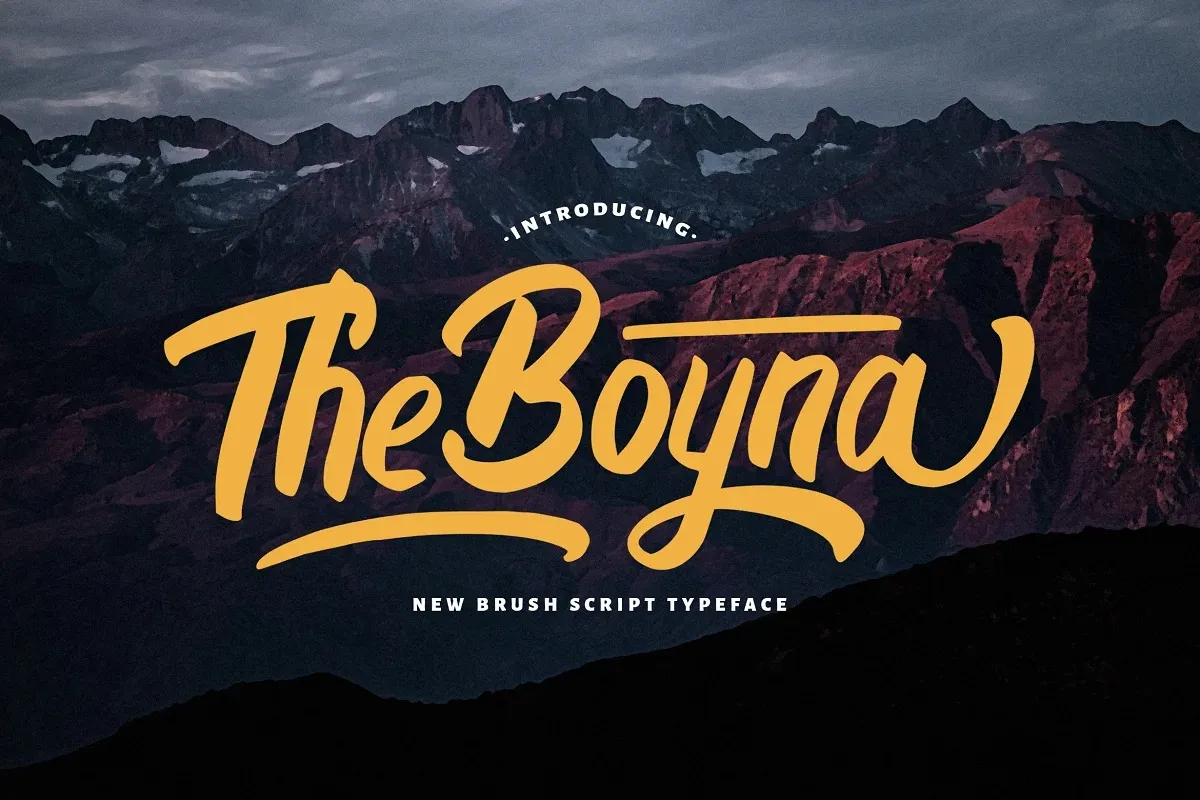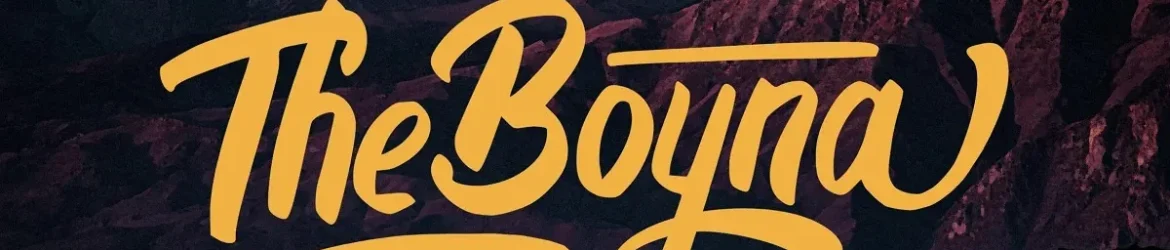
A ‘Boyna Font’ é uma aquarela script feita para quem busca uma escrita natural e casual, ideal para ambientes criativos e versáteis. Escrevida com pincéis sobre papel, então cuidadosamente trazida de volta à forma vetorial, essa fonte possui letras curvadas, arredondadas e carrega um estilo vintage único e sofisticado. Suas linhas fluidas fazem dela uma escolha perfeita para qualquer marca que busca personalidade e elegância em sua identidade visual. Descubra como ela pode fazer seus ideais mais criativos despertar vida! Esta fonte pertence à categoria de ‘Script Fonts’ no site 99designs, um local conhecido por oferecer uma ampla variedade de opções para os designers e criadores de conteúdo.